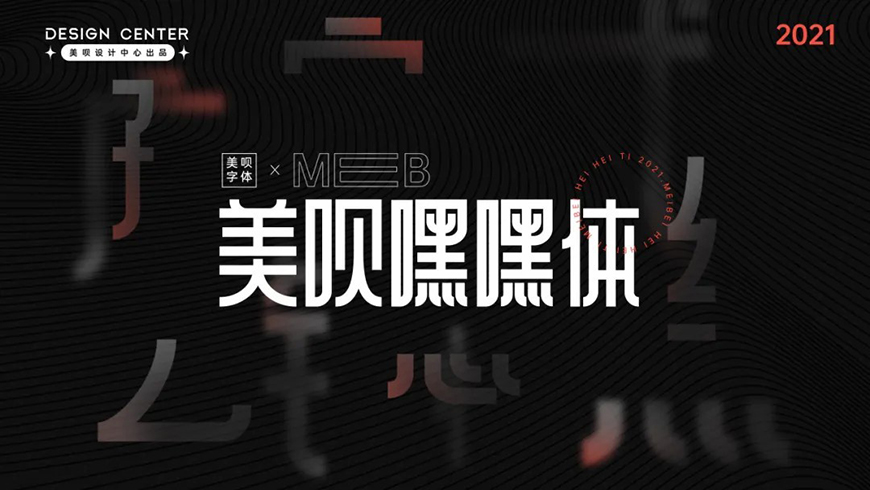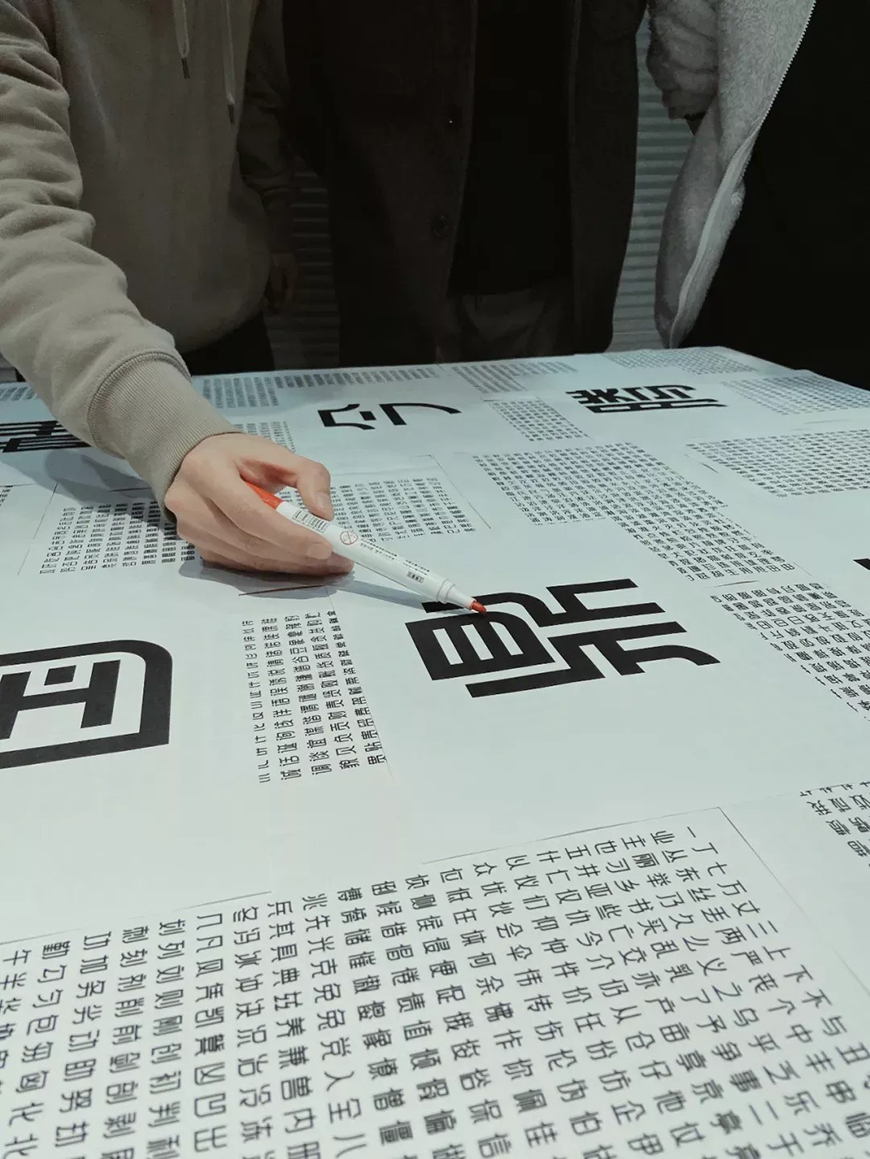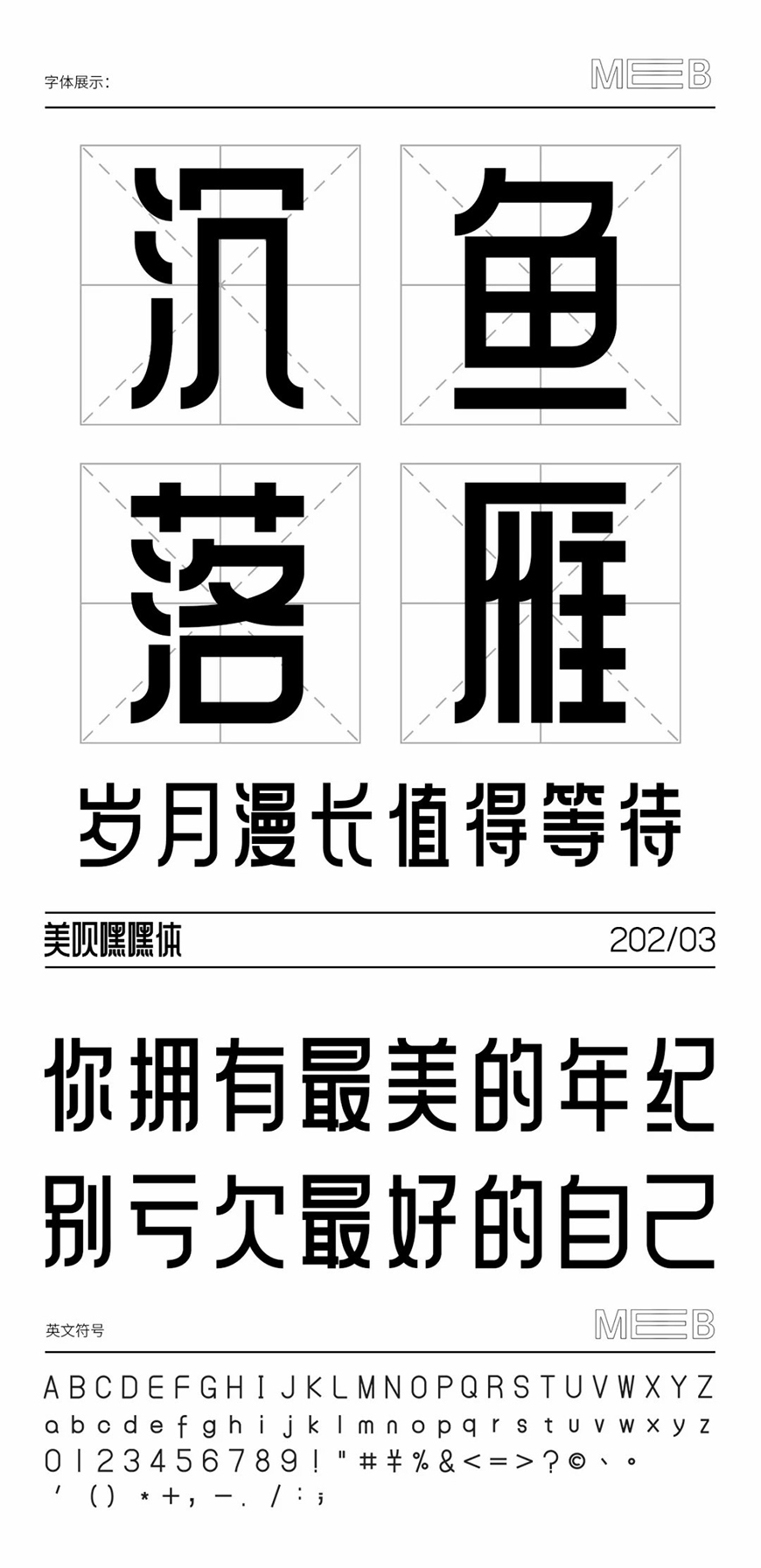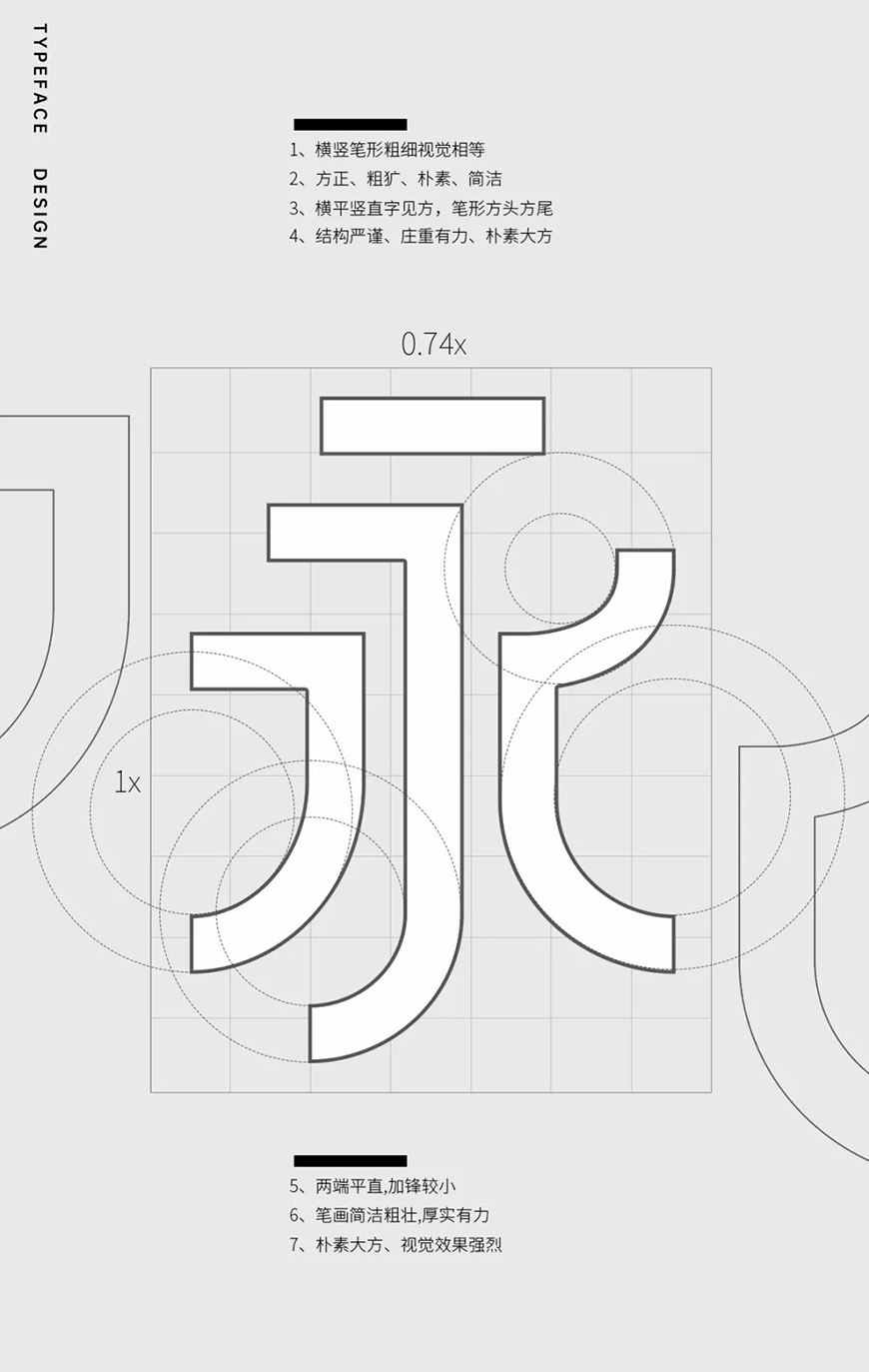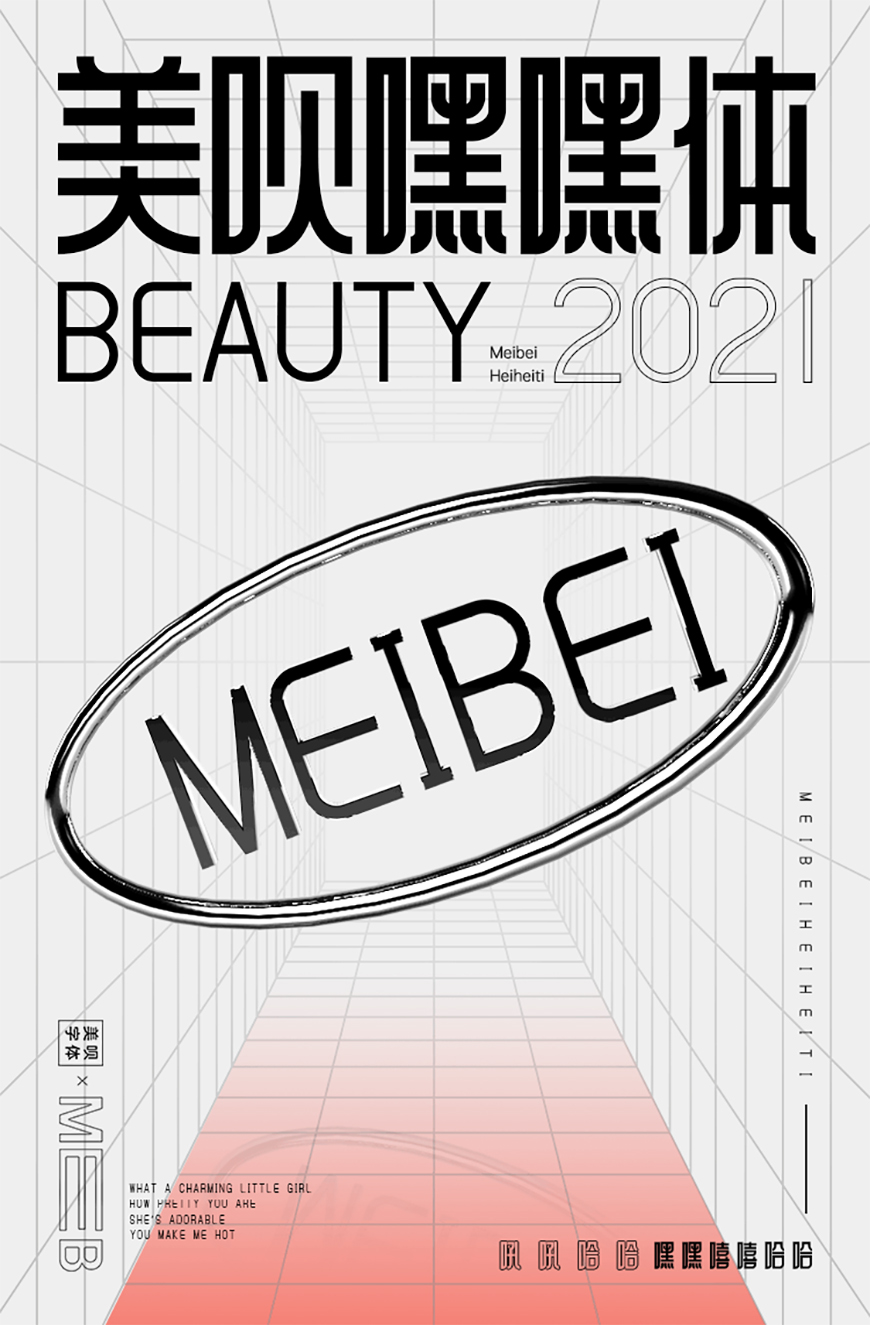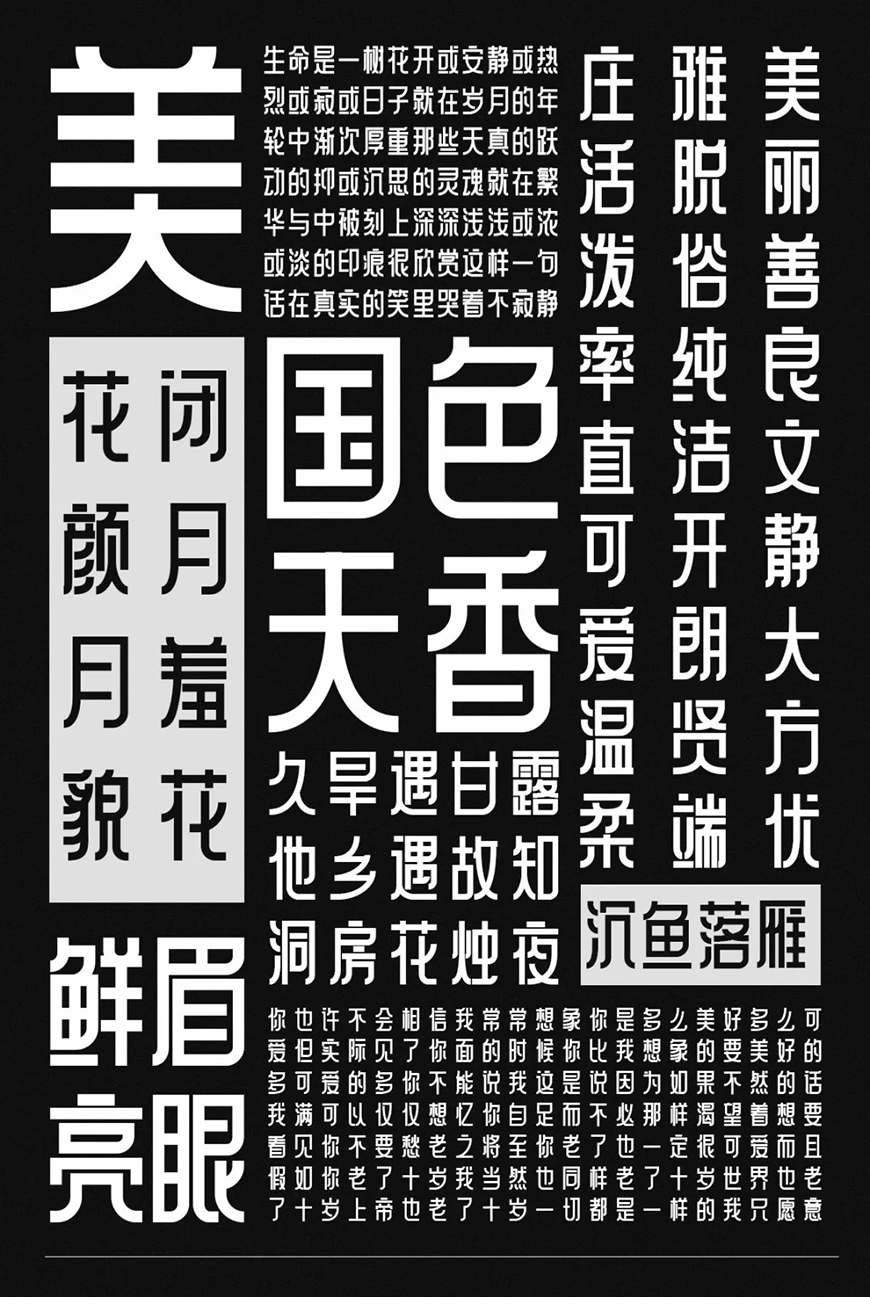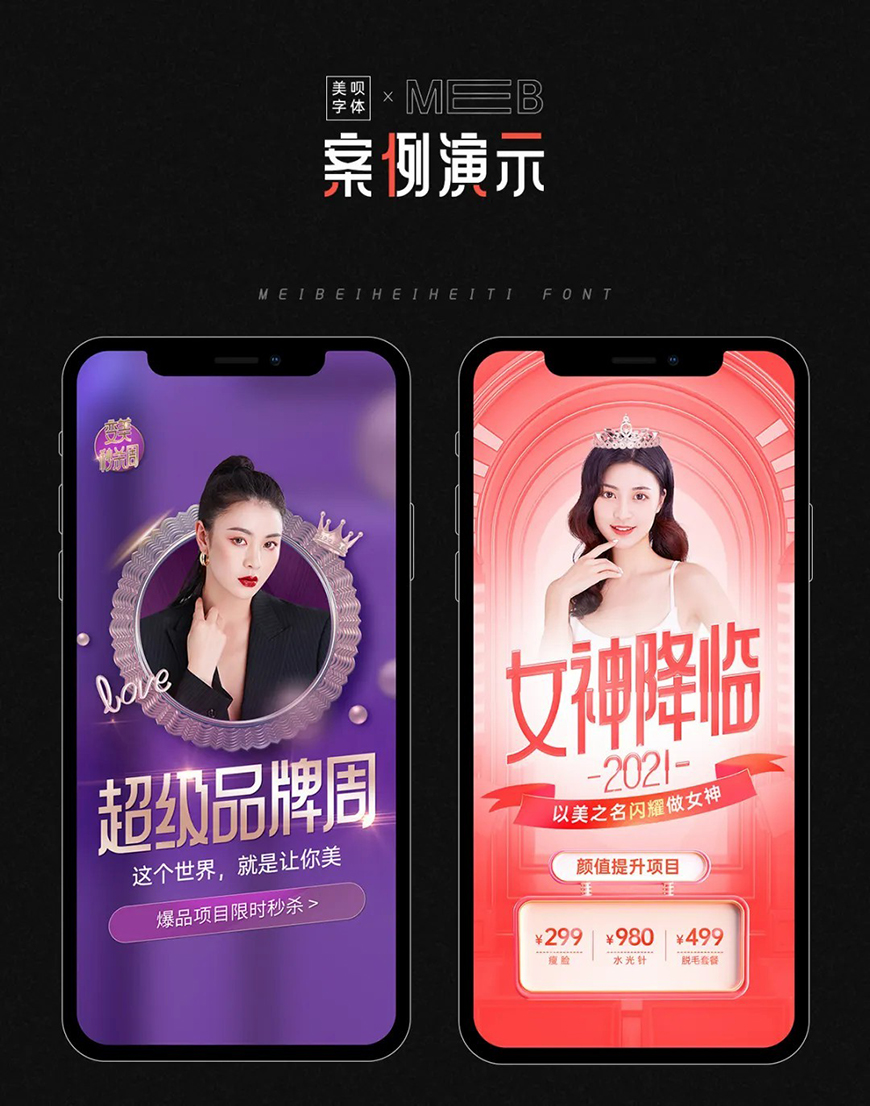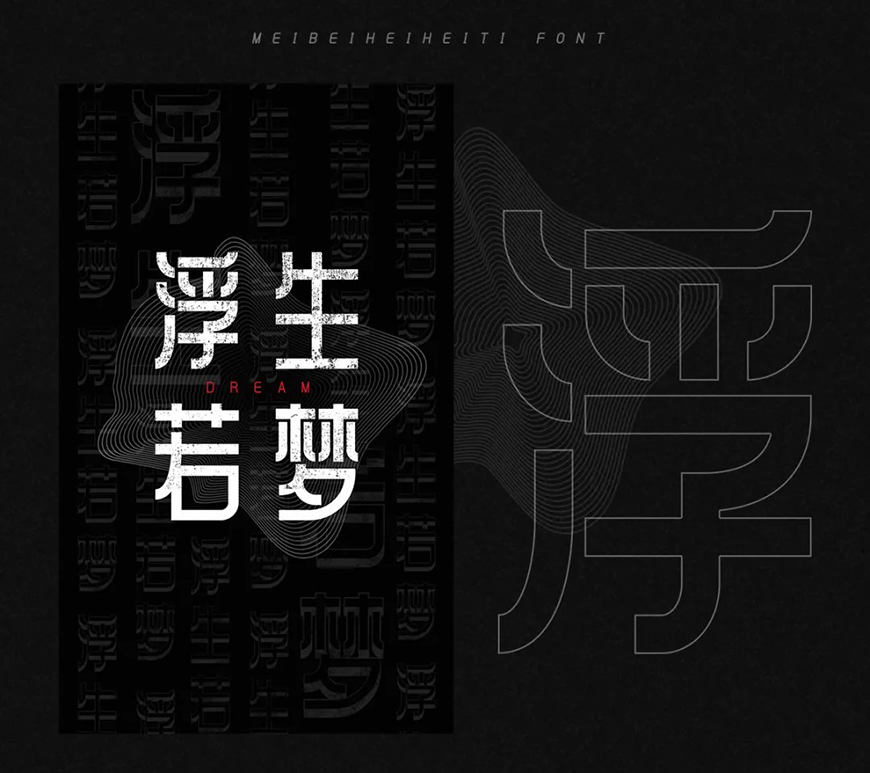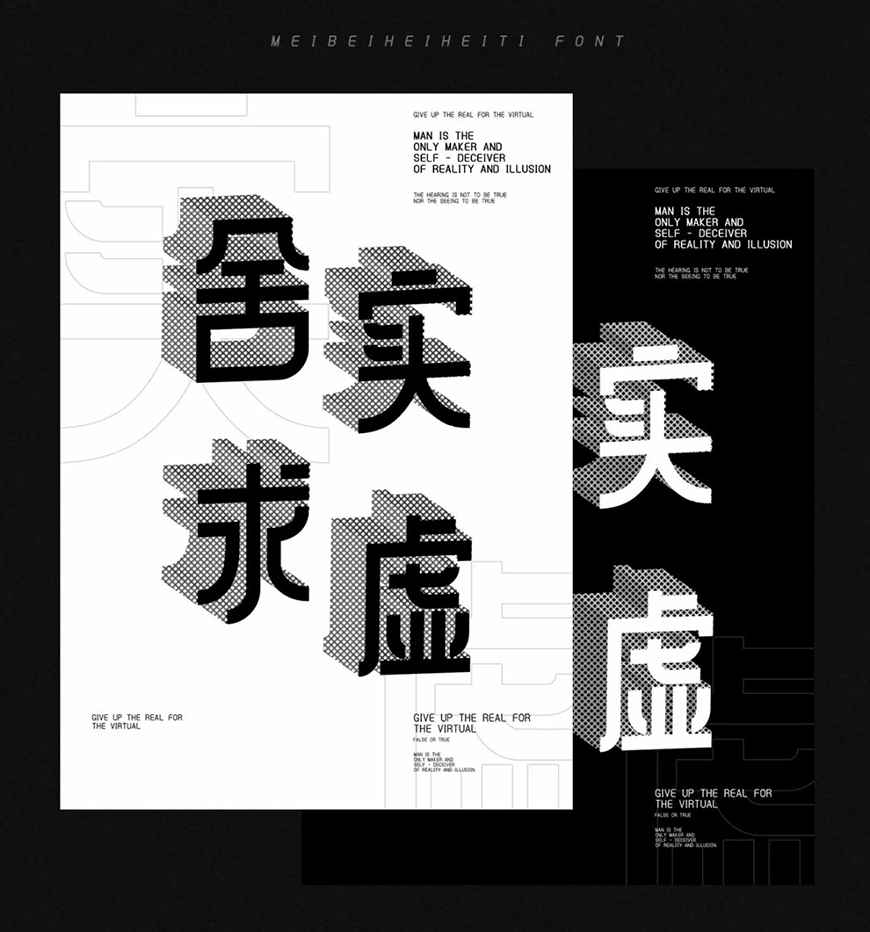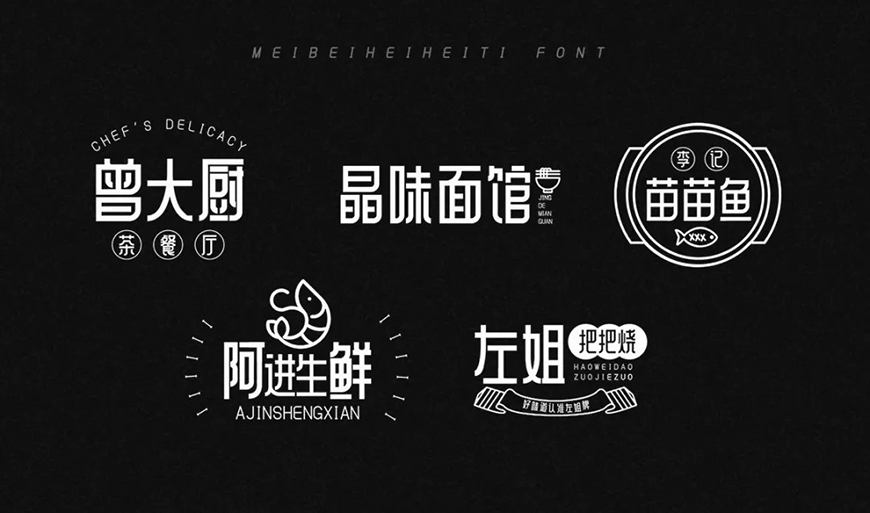
美呗嘿嘿体
美呗嘿嘿体由美呗设计团队基于品牌视觉表达需求所开发,整体目标是强化品牌识别度与符号感。在设计过程中延续了团队“开放、合作、创新”的核心价值理念,使字体不仅具备基础排版功能,同时也承担一定的品牌传播属性。该字体诞生于团队非正式创作时间阶段,并经过多轮版本迭代与细节修正,在完成度与稳定性上具备较高水准。
从字形结构来看,美呗嘿嘿体整体采用横平竖直的构建逻辑,字面比例偏规整,重心稳定,呈现出较强的秩序感与统一性。笔画处理上以方头方尾为主要特征,转折处干净利落,减少多余装饰,使视觉表达更为直接。整体笔画粗细接近等值处理,增强了版面中的块面感与存在感,在标题环境中具有较强的视觉抓取能力。
在细节风格上,该字体适度控制加锋与装饰变化,使其在保持力量感的同时不过度张扬,呈现出一种简洁、厚实且偏理性的视觉气质。这种设计方式让字体在信息传达中更偏向“稳定表达”,而非情绪化表现,因此在商业标题、品牌主视觉、活动海报等场景中具有较高适配度。
从应用层面来看,美呗嘿嘿体当前收录约2500个常用汉字,基本能够覆盖常见标题与基础传播需求。在电商展示、品牌活动页、社交媒体封面等场景中,能够有效提升文字的识别度与画面整体统一性,尤其适合需要强调“简洁有力”视觉风格的设计项目。
总的来说,美呗嘿嘿体是一款结构规整、笔画简洁且视觉力量感较强的标题类字体,在保持实用性的基础上强化了品牌表达能力,适用于多种商业与设计场景。
字体设计师/发行商
美呗